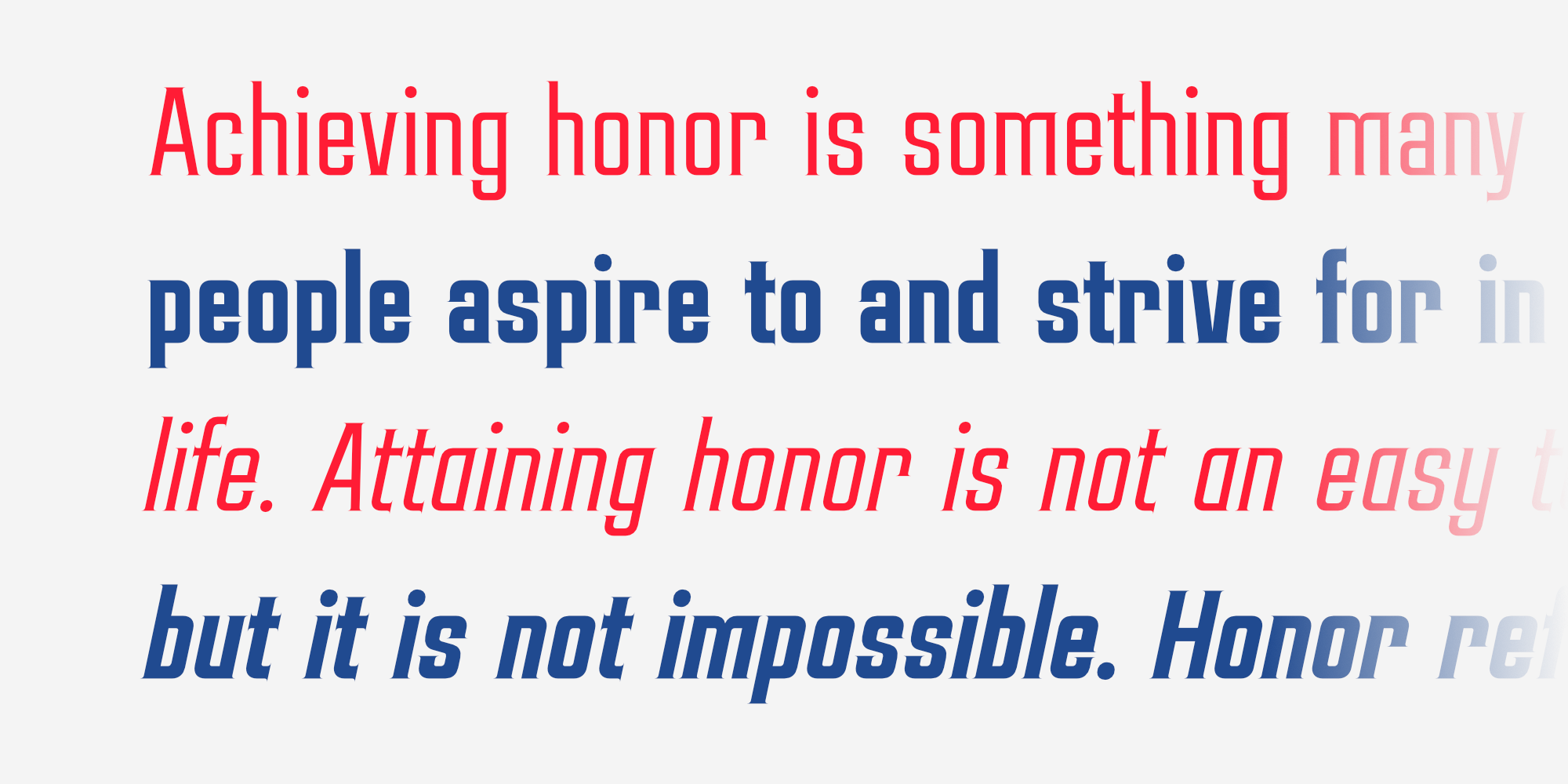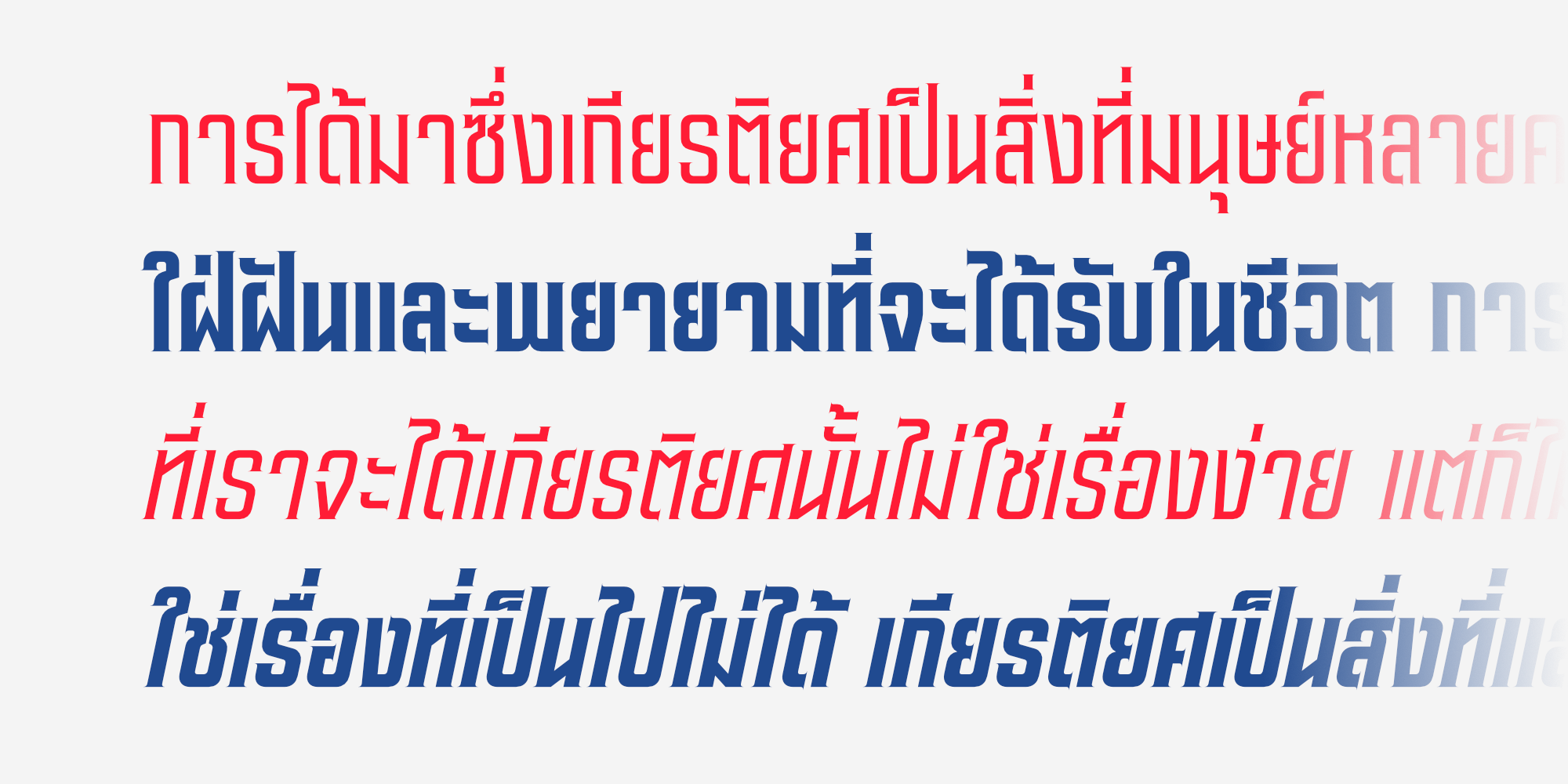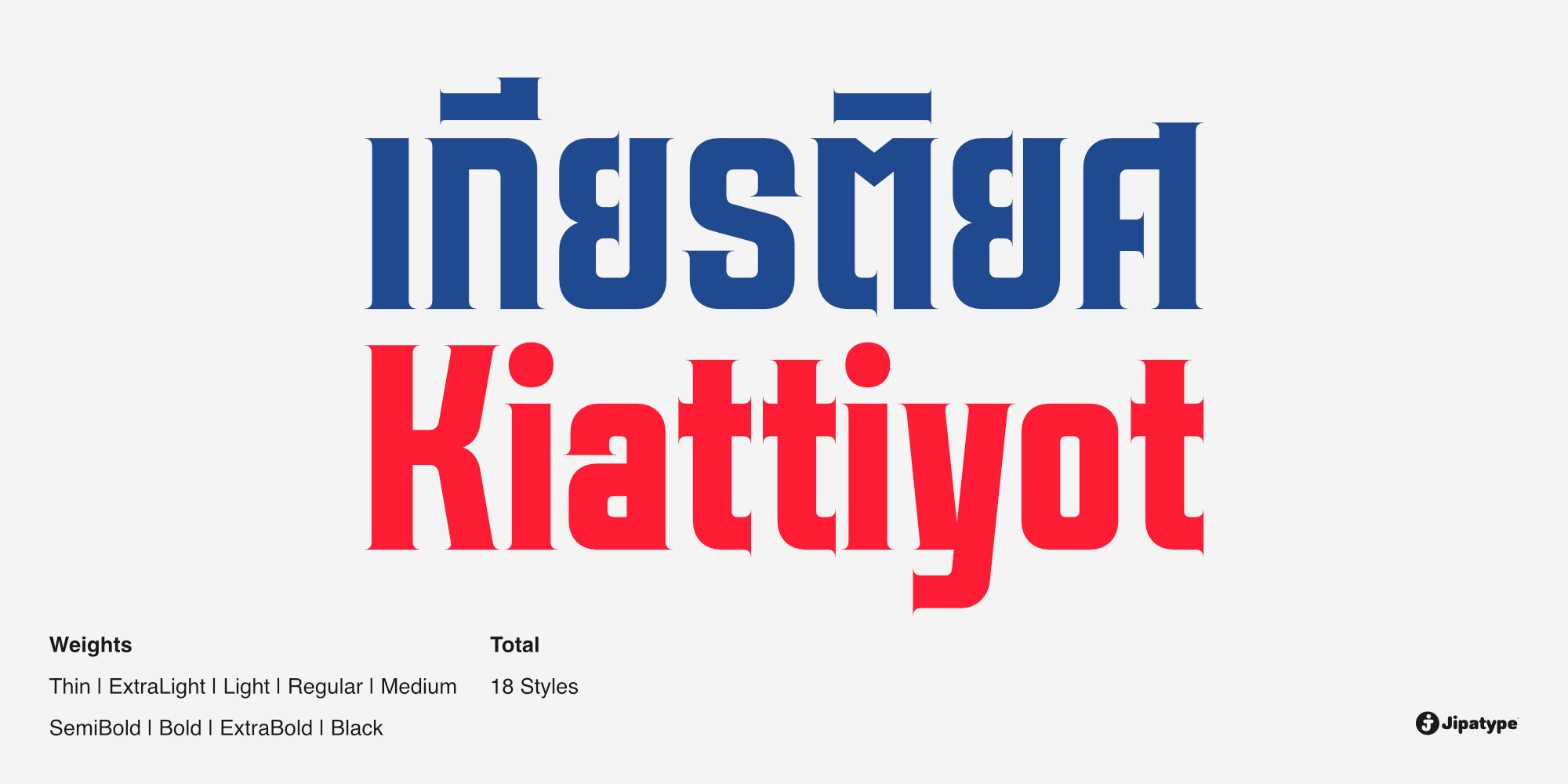
เกียรติยศ | Kiattiyot
เกียรติยศ เป็นแบบอักษรมีเชิงที่เล็กและคมเป็นพิเศษ ด้วยเส้นสายที่คมชัดและโครงสร้างที่แข็งแรง เหมาะสำหรับงานที่ต้องการความทันสมัยและความโดดเด่น ไม่ว่าจะเป็นงานออกแบบโลโก้สำหรับแบรนด์กีฬา หรือโปสเตอร์สำหรับงานอีเวนต์ แบบอักษรนี้ประกอบด้วย 18 รูปแบบ ครอบคลุมน้ำหนักเส้นตั้งแต่บางที่สุดจนถึงหนาที่สุด โดยรองรับทั้งชุดอักษรลาติน 1 และอักษรไทย